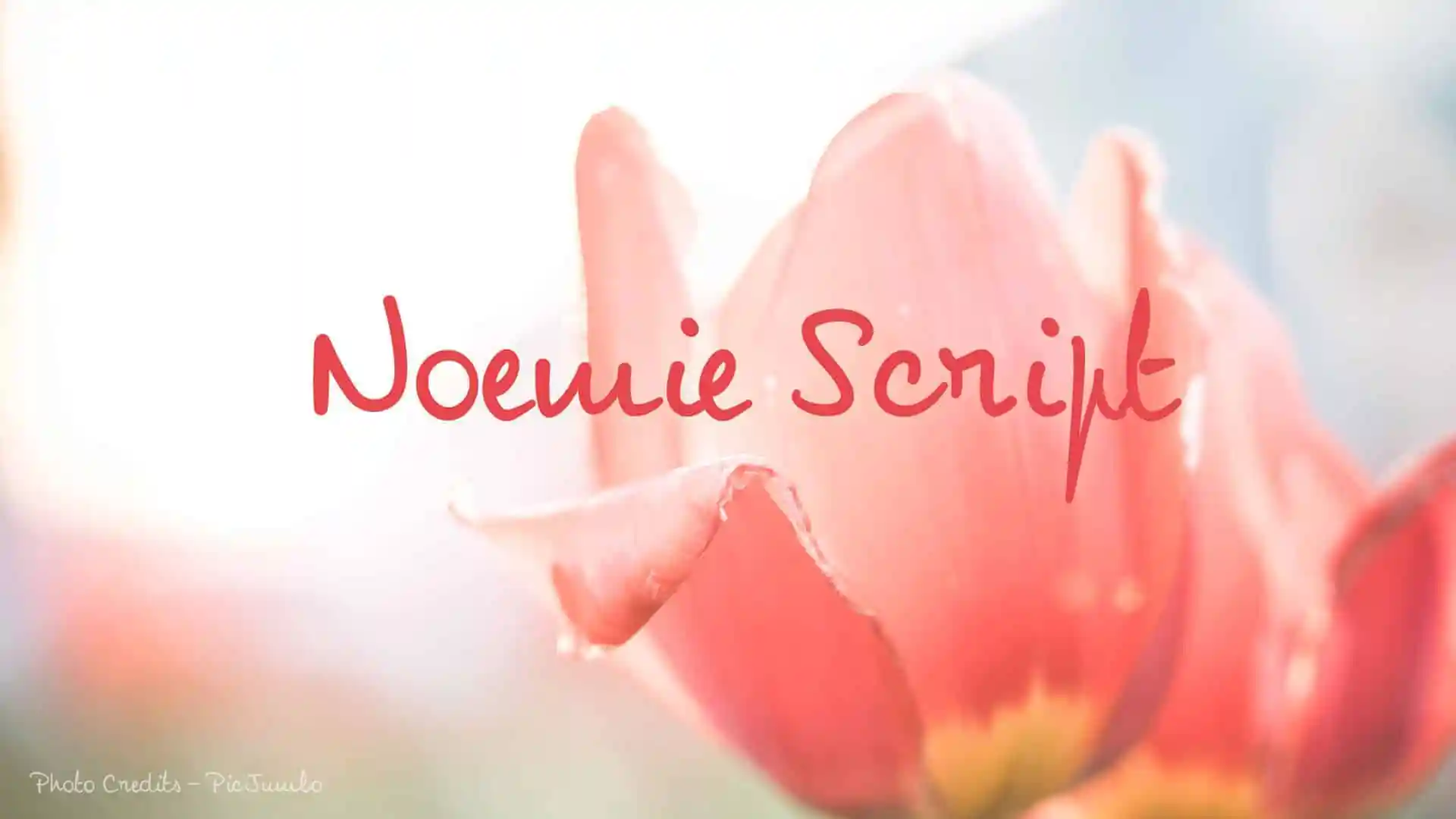
Noemie Script Font – Download Grátis
A Noemie Script é uma fonte script criada pelo designer SvNProd. Ela se inspira no estilo das escritas manuscritas, com suas linhas levemente irregulares e textura ressaltando a atmosfera de um pincel de calligrafia em papel. Esta fonte apresenta alternativas estilísticas para letras iguais, ligaturas descontínuas e muitos outros detalhes que tornam o texto personalizável e sofisticado. O resultado é uma fonte versátil adequada para se tornar o principal ator de qualquer design, seja ela usada em textos legíveis ou trabalhando como um elemento visual para destacar visivelmente. A Noemie Script tem um toque natural e elegante que a torna perfeita para aplicativos variados, desde cartões de convite até websites responsivos. Ela é a escolha ideal para aqueles buscando uma fonte script com estilo autêntico e textura suave, certificada por sua grande variedade de personalização disponíveis. É uma ótima opção para quem busca um toque único para seus projetos digitais.